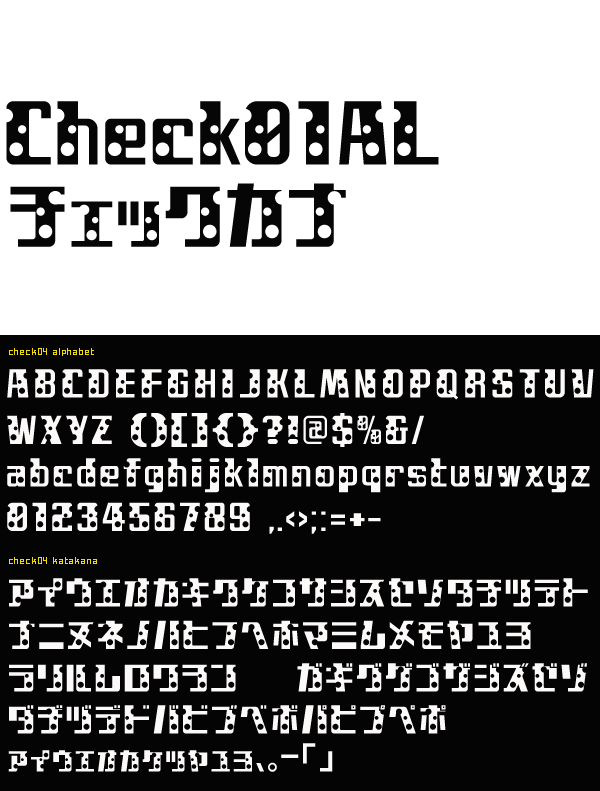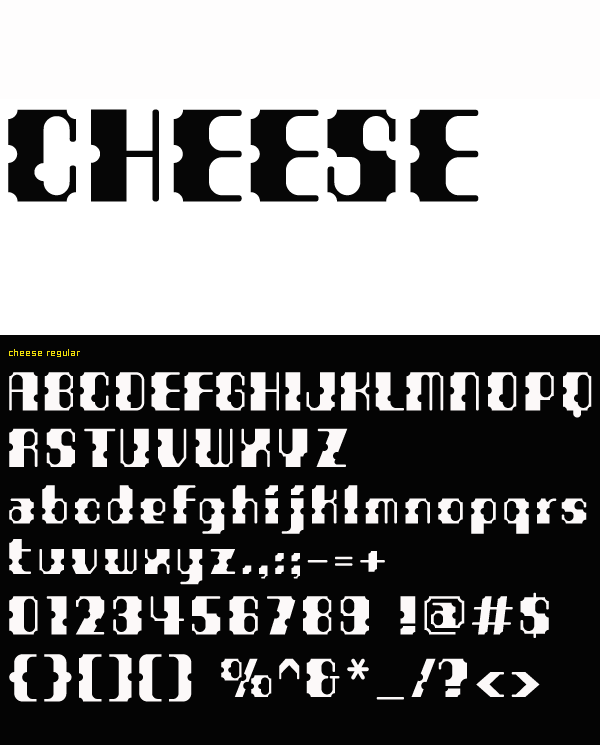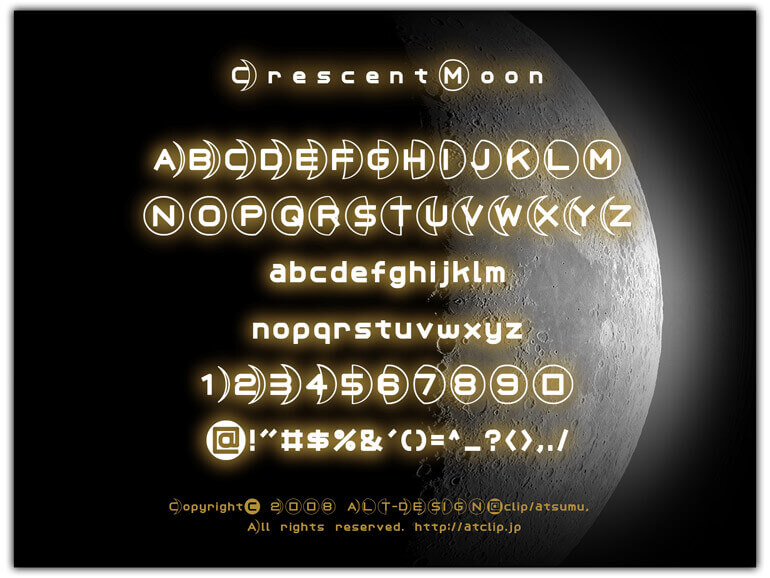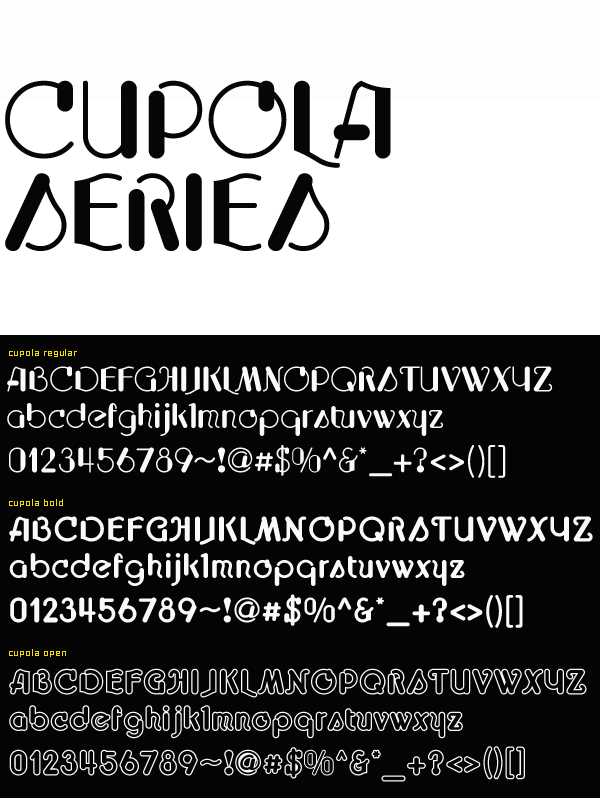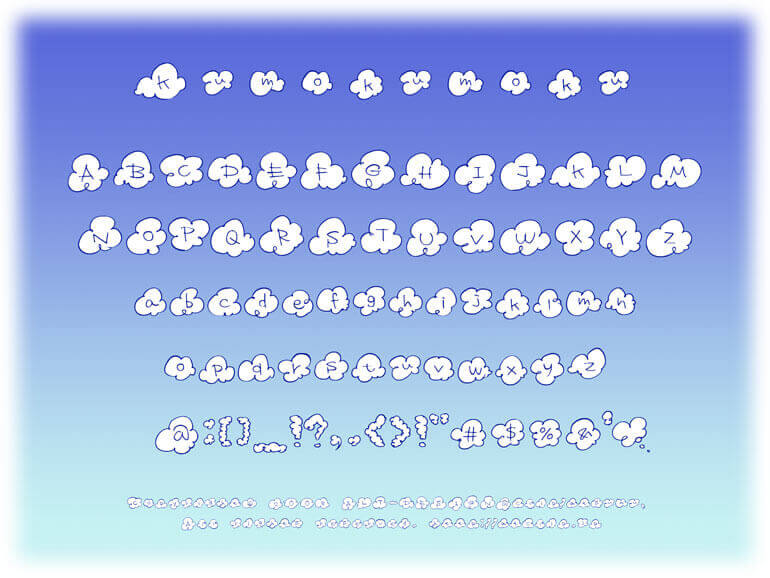
無料でダウンロードできるユニークなフォント31個まとめ
無料でダウンロードできるフォントの中から、ユニークなフォントを31個まとめました。遊びの要素を取り入れた個性的なフォントや、ロゴなどに使えばインパクトがあるフォントを集めています。
Acidpunk
迫力のあるトゲトゲしたパンキッシュなフォント。音楽イベントやタイトルロゴなどで、迫力のあるダイナミックなイメージを演出するときにおススメです。
Airline-AL, KT, HR
太文字の個性的なフォント。文字によっては判読が難しいですがそこに面白味があるかもしれません。
Ball-AL
フォント名の通り、ボールの中に文字が入っているフォント。
Blockbox 3D
立方体から切り出した奥行きのある3Dフォント。ロゴでの利用やデザインのアクセントになります。
Box-AL
フォント名の通り、立方体の箱の中に文字が入っているフォント。
Button-AL
フォント名の通り、立体的なボタンに文字が入っているフォント。
Check 04 AL&kana
チェック柄のようにデザインされたフォント。
Cheese Bold
チーズをイメージして凸凹な雰囲気が出ているフォント。
Children
子供が書いたようにかわいらしいイメージを表現できるフォント。子供向けの商品やゲームなどに適します。
CresentMoon
月の満ち欠けをフォントで表現しています。
Cupola Series
文字の線幅を極端に変えることで特徴的なフォントになっています。
ecoco
エコマークのように地球にやさしいフォント。
GL-Grimoire-MajKey
ヨーロッパで流布していた魔術書(グリモア/グリモワール)より英国の魔術師マグレガー・メイザースが編集・出版したグリモア「ソロモン王の鍵」に出てくる惑星護符のフォント。
GL-Grimoire-MinKey
ヨーロッパで流布していた魔術書(グリモア/グリモワール)より英国の魔術師マグレガー・メイザースが編集・出版したグリモア「ゲーティア」で紹介されているソロモン72柱の精霊の紋章のフォント。
Globo-AT
立体的な球体に文字が貼られているコミカルなフォント。
Korrekt
現代のファッションや音楽を感じさせるフォント。
Kumokumoku
フォント名の通り、もくもくとした雲の中に文字が入っているフォント。